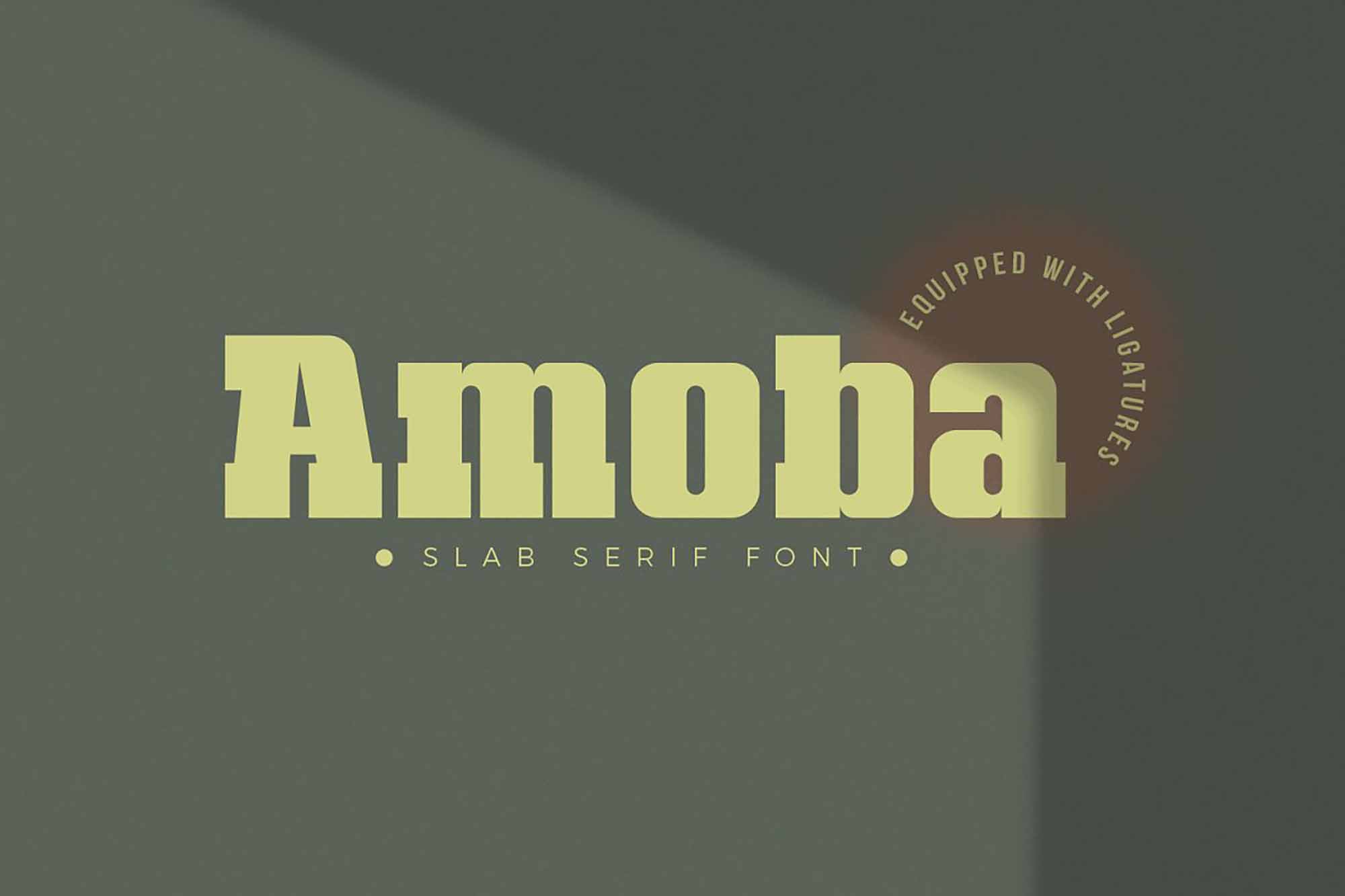
A Amoba Slab Serif é uma fonte serif que se destaca entre as demais, oferecendo uma aparição vibrante e deslumbrante. Se você é um fanático por fontes serif, com certeza vai apreciar a Amoba. Esta fonte slab serif, que se diferencia notavelmente das demais serif, está repleta de personalidade e vigor. Ela faz parte da paleta de recursos gráficos do Fontesrepo, onde você pode encontrar uma ampla variedade de fontes para ilustrar seus projetos. Se você se identifica como um profissional que valoriza a seriedade e o estilo de uma fonte serif, a Amoba é certamente uma ótima opção. Com sua forte presença visual, a Amoba trará alegria e aconchego a qualquer página de design. Se você está em busca de uma fonte que traga alegria e um toque de originalidade ao seu projeto, a Amoba Slab Serif é uma excelente escolha.